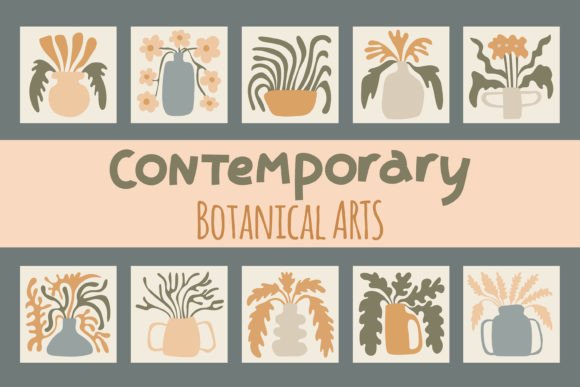
Contemporary Botanical Arts
Contemporary Botanical Artsのような高品質の素材をお探しの場合、このプレミアムパッケージはクリエイティブなプロジェクトに素晴らしい選択です。
POD(オンデマンド印刷)製品、結婚式の招待状、またはソーシャルメディアのグラフィックを作成している場合でも、Contemporary Botanical Artsは理想的です。